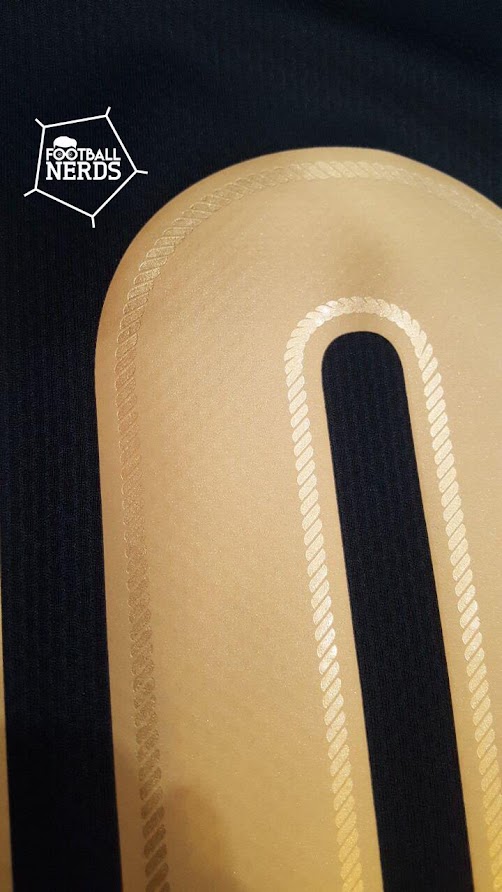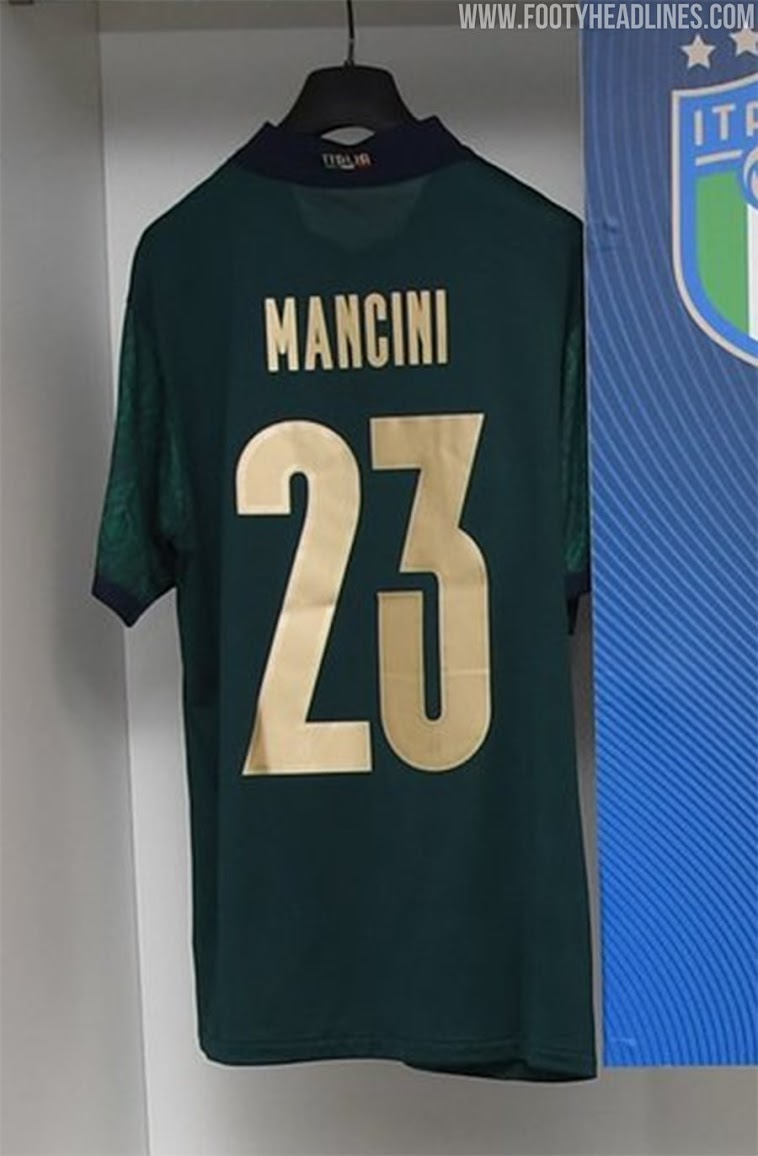
Stilvolle Puma Italien "Renaissance" Trikot-Schriftart Enthüllt
Update: Italien hat gestern Abend das brandneue 2019-2020 Trikot debütiert. Dies ermöglicht uns auch einen Blick auf mehr Beispiele der neuen Italien 2020 Trikot-Schriftart - wir wissen bisher nicht, ob die Schriftart auch bei der EURO 2020 verwendet wird.
Puma Italien "Renaissance" Trikot-Schriftart
Die neue Schriftart, die von Puma für das Italien "Renaissance" Ausweichtrikot entworfen wurde, ist absolut atemberaubend. Bilder via @football_nerds.
Die Schriftart ist golden, passend zu den Logos auf der Vorderseite. Es gibt ein subtiles Randdetail, das von Zierstickereien inspiriert ist, die in der Renaissance verwendet wurden. Das FIGC-Wappen, das ebenso dezent eingesetzt wird, rundet den Look ab.